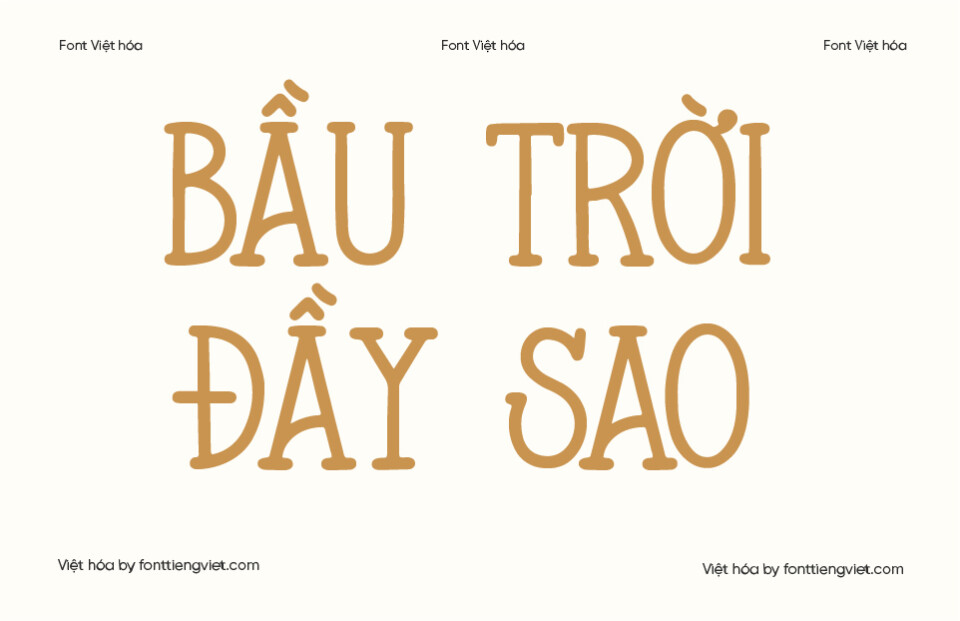
Font 1FTV VIP Star Light Việt Hóa – Font Có Chân Dễ Thương Cho Sách Trẻ Em
Giới thiệu về Font 1FTV VIP Star Light Việt Hóa – Font Có Chân Dễ Thương Cho Sách Trẻ Em
Trong thế giới thiết kế đồ họa dành cho giáo dục và thiếu nhi, việc lựa chọn một bộ Font Miễn Phí phù hợp đóng vai trò quyết định đến khả năng tiếp nhận ngôn ngữ của trẻ nhỏ. Font 1FTV VIP Star Light Việt Hóa – Font Có Chân Dễ Thương Cho Sách Trẻ Em chính là một giải pháp hoàn hảo, kết hợp giữa sự chuyên nghiệp của kiểu chữ có chân (serif) và nét mềm mại, đáng yêu cần thiết cho các ấn phẩm dành riêng cho học sinh. Bộ font này không chỉ đơn thuần là công cụ trình bày văn bản mà còn là cầu nối cảm xúc, giúp các trang sách trở nên sinh động và lôi cuốn hơn đối với các em nhỏ trong độ tuổi khám phá thế giới xung quanh.
Tại sao nên chọn Font 1FTV VIP Star Light Việt Hóa cho thiết kế giáo dục?
Đặc điểm thiết kế tinh tế và thân thiện
Đặc trưng lớn nhất của Font 1FTV VIP Star Light Việt Hóa – Font Có Chân Dễ Thương Cho Sách Trẻ Em nằm ở cấu trúc chân chữ (serif) được bo tròn tinh tế. Khác với các font serif truyền thống thường mang lại cảm giác nghiêm túc và cứng nhắc, bộ font này đã được tinh chỉnh để tạo ra sự thân thiện tuyệt đối. Các nét chữ có độ dày vừa phải, tạo cảm giác thanh thoát nhưng vẫn rất vững chãi trên mặt giấy. Đây là yếu tố cực kỳ quan trọng giúp các bé không bị mỏi mắt khi đọc những đoạn văn dài trong sách giáo khoa hoặc truyện tranh cổ tích.
Khả năng đọc hiểu vượt trội cho trẻ em
Khoa học giáo dục đã chứng minh rằng trẻ em dễ dàng ghi nhớ mặt chữ hơn khi các ký tự có sự phân biệt rõ ràng. Font 1FTV VIP Star Light Việt Hóa – Font Có Chân Dễ Thương Cho Sách Trẻ Em sở hữu khoảng cách giữa các chữ cái (kerning) được tối ưu hóa, giúp ngăn chặn tình trạng dính chữ thường gặp ở các font thiết kế không chuyên. Việc việt hóa hoàn chỉnh với đầy đủ các dấu thanh chuẩn tiếng Việt giúp bộ font này hiển thị mượt mà trên mọi nền tảng, từ bản in trực tiếp đến các bài giảng trình chiếu trên lớp học điện tử.
Ứng dụng thực tế của bộ font trong trường học và đời sống
Thiết kế sách truyện và tài liệu học tập
Với phong cách dễ thương, bộ font này cực kỳ phù hợp để làm tiêu đề chương hoặc nội dung chính cho các bộ sách kỹ năng sống, sách tô màu và truyện ngụ ngôn. Sự hiện diện của Font 1FTV VIP Star Light Việt Hóa – Font Có Chân Dễ Thương Cho Sách Trẻ Em giúp trang sách bớt đi sự khô khan, thay vào đó là một không gian sáng tạo đầy màu sắc, kích thích trí tưởng tượng của các em học sinh ngay từ cái nhìn đầu tiên.
Trang trí không gian lớp học và thiệp mừng
Bên cạnh mảng xuất bản, các thầy cô giáo có thể sử dụng bộ chữ này để thiết kế bảng biểu, nội quy lớp học hoặc các tấm thiệp khen ngợi học sinh. Nét chữ Star Light mang lại cảm giác ấm áp, khích lệ, rất phù hợp với môi trường sư phạm nhân văn tại Việt Nam hiện nay.
Kết luận và trải nghiệm người dùng